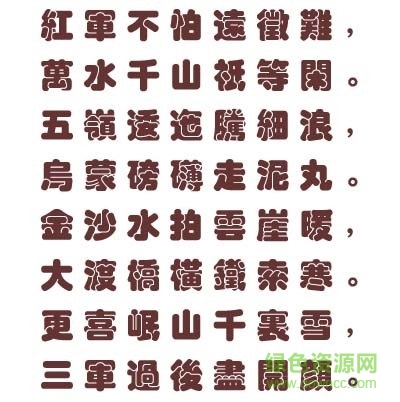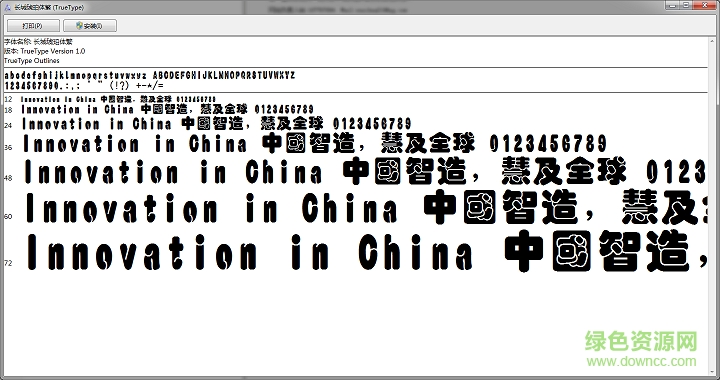
長城琥珀體繁是一款很有創(chuàng)意的繁體字體。字體重疊的部分邊線都是白色,非常突出,也是字體最大的亮點,繁體加上琥珀體,更加的生動可愛,喜歡的朋友,趕快來綠色資源網(wǎng)下載體驗吧!
1.中國的字體設(shè)計是在印刷術(shù)的產(chǎn)生和發(fā)展中應(yīng)運而生的。在古代,中國的字體設(shè)計曾有過輝煌的歷史時期,在宋朝時進(jìn)入黃金時代。
2.清朝末年,鉛字排版印刷術(shù)傳入中國,字體設(shè)計進(jìn)入鉛字時代。這個時期的字體設(shè)計既要帶有傳統(tǒng)文化的審美慣性,又要符合鉛字印刷的工藝要求,字體設(shè)計走到了轉(zhuǎn)折的關(guān)口。
3.鉛字印刷是印刷走入機械化、工業(yè)化時代的標(biāo)志,但在這一時代里,印刷字體設(shè)計卻始終無法超越手工勞動的制約,無法擺脫刻模、鑄字、撿字、排版等一系列印前繁雜工藝的束縛